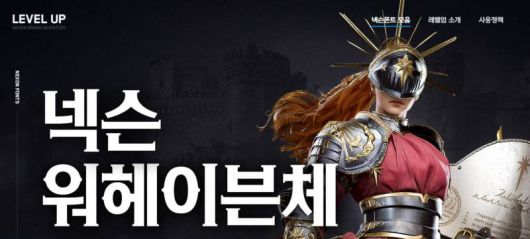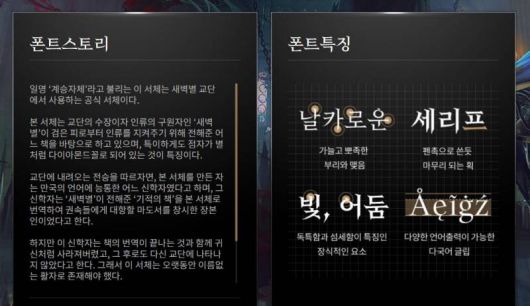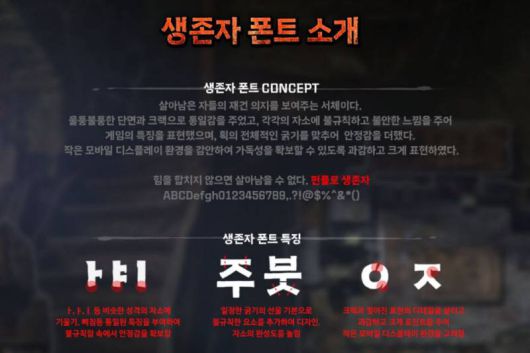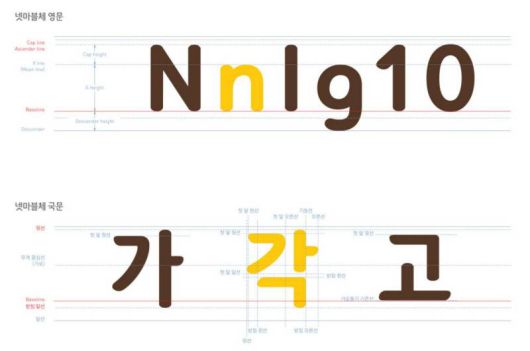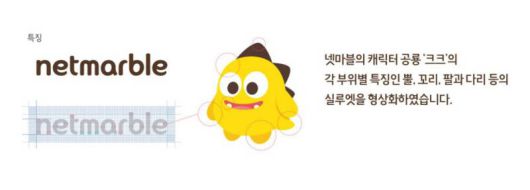
먼저, 넥슨은 ‘레벨업’이라는 폰트 배포 홈페이지를 통해 무려 8종의 자체 제작 폰트를 제공한다.
8개의 폰트 중 ‘워헤이븐체’, ‘던파 연단된 칼날’, ‘던파 비트비트 v2’, ‘넥슨 배찌체’, ‘넥슨 풋볼 고딕’, ‘메이플스토리 서체’는 장식적인 요소가 강해 제목이나 포인트 글자를 강조하는 데 사용하기 적합하다. 각각 넥슨이 서비스하는 게임을 기반으로 제작됐고, 종류가 많은 덕분에 강인한 느낌, 귀여운 느낌 등 상황에 맞는 폰트를 골라 응용하기 좋다.
이어서, ‘넥슨 Lv.1 고딕’, ‘넥슨 Lv.2 고딕’은 깔끔하고 단정한 느낌이 강해, 글자를 많이 적게 되는 본문에 사용해도 가독성이 뛰어나다. 두 서체는 서로 큰 차이는 없으나, ‘넥슨 Lv.2 고딕’이 ‘넥슨 Lv.1 고딕’보다 글자의 장평이 짧아 비교적 좁은 공간에 더 많은 글자를 적을 수 있다.
빛의 계승자체 |
다음으로, 컴투스홀딩스도 자회사인 펀블로를 통해 ‘빛의 계승자체’와 ‘생존자체’를 배포했다.
‘빛의 계승자체’ 먼저 살펴보자면, 동명의 모바일 게임을 기반으로 제작된 이 폰트는 펜촉으로 적은 것처럼 획마다 장식적인 삐침(부리)이 있는 것이 특징이다. 특유의 화려한 느낌이 인기가 많아 로맨스 판타지 장르 웹소설 타이포그래피에 활용되는 경우도 잦고, 베스트셀러 도서인 ‘달러구르트의 꿈 백화점’의 표지에도 활용된 바 있다. 개인적인 경험으로는 어두운 배경의 PPT나 포트폴리오에 밝은 톤으로 폰트를 삽입했을 때 장식적인 요소가 도드라지며 가장 예쁘게 나왔다.
생존자 폰트 |
‘생존자체’도 ‘빛의 계승자체’와는 다른 방향으로 독특한 매력을 가진 폰트다. 이 폰트는 자사가 개발한 모바일 게임 ‘워킹데드: 올스타즈’를 기반으로 제작되어 게임의 분위기에 걸맞은 울퉁불퉁한 글자와 크랙과 찢어진 표현으로 디테일을 살렸다. 큼직큼직하고 굵게 뻗은 느낌이 강해 자료의 제목에 쓰기 적절하다.
넷마블체 |
자사의 게임을 기반으로 제작한 폰트가 아니라, 게임사의 마스코트 이미지를 폰트화 한 경우도 있다. 넷마블이 배포한 ‘넷마블체’가 그렇다.
넷마블은 넷마블 캐릭터 ‘ㅋㅋ’를 모티브로 하여 각 부위별 특징을 폰트로 형상화했다고 설명했다. 동글동글한 하고 귀여운 공룡의 뿔과 꼬리, 팔과 다리 등의 실루엣을 따 중심부의 무게감과 끝 부분의 꼬리 같은 장식적인 획이 나온 것.
넷마블체 |
전체적으로 둥글고 부드러운 느낌이 있어서 비슷한 분위기의 작업물에 잘 어울릴 것 같고, 본문과 제목 어느 쪽에 사용해도 괜찮을 만큼 범용성이 좋다.